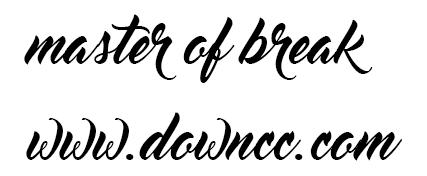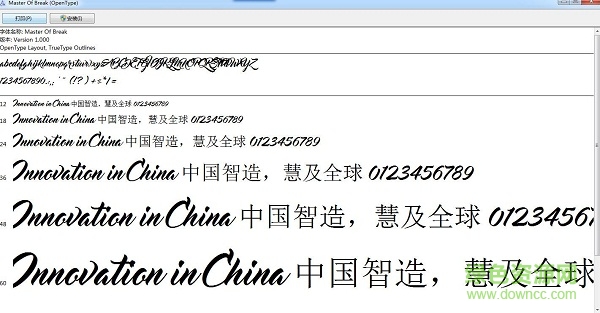
master of break font
master of break字體是一款流暢優(yōu)雅的英文藝術(shù)字體,風(fēng)格獨(dú)特,氣質(zhì)浪漫,筆形富于變化,適用于廣告制作、海報(bào)設(shè)計(jì)、影視、游戲等等各個(gè)方面,喜歡的朋友快來(lái)下載吧!